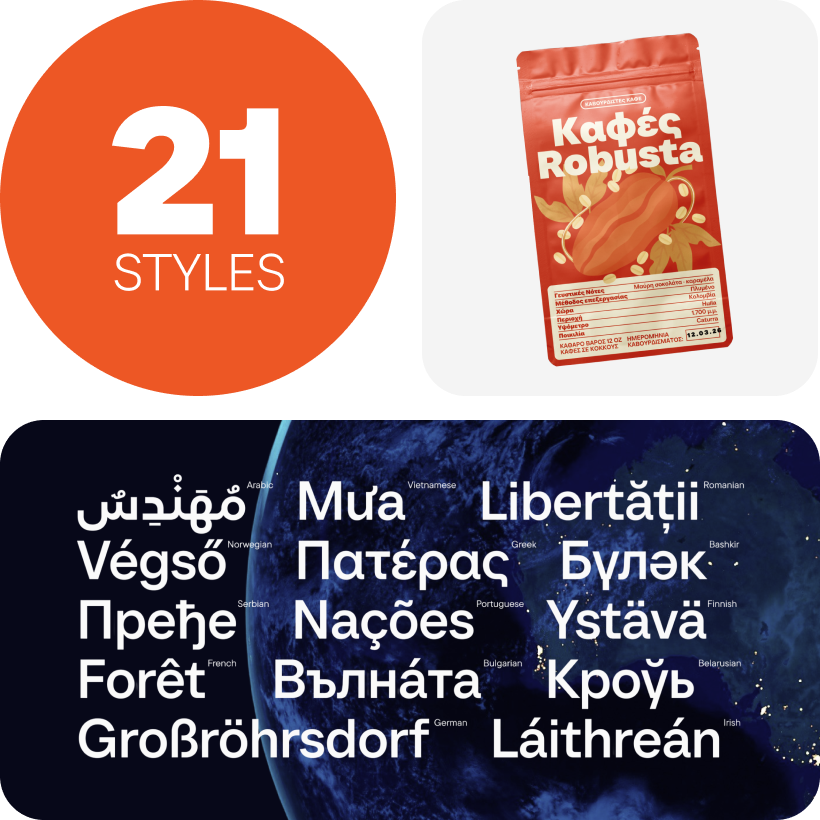
Шрифты для постеров к фильмам
TT Norms® Pro — TT Нормс Про
TT Norms® Pro — функциональный геометрический гротеск для эстетичных решений, бестселлер студии TypeType. Это стильный, лаконичный и универсальный шрифт, который станет полноценной базой для вашей коллекции.
TT Commons™ Pro — TT Коммонс Про
TT Commons™ Pro — геометрический гротеск. Один из самых востребованных шрифтов студии, получивший признание за счёт универсального характера, объёмного кассового состава с поддержкой более 280 языков и функционального набора OpenType фич.
TT Hoves Pro — ТТ Ховс Про
Произносится «ТТ Ховс Про». «Hoves» — производное слово от horizontal (с английского «горизонтальный») и vertical (с английского «вертикальный»). «Pro» произносится как «про», и является разговорным сокращением слова «профессиональный». Буквы «TT» являются аббревиатурой названия компании.
TT Hoves Pro — один из бестселлеров нашей студии, входящий в «базовую» коллекцию универсальных шрифтов. Это скандинавский гротеск с нейтральным, и при этом узнаваемым характером.
TT Odellia — ТТ Оделлия
Произносится «ТТ Оделлия». Слово «Odellia» — производное от имён Одетта и Одиллия из балета «Лебединое озеро». Буквы TT являются аббревиатурой названия компании.
TT Odellia — старостильная антиква с современным рисунком, вдохновлённая венецианскими шрифтами и классической музыкой.
TT Nooks Serif — ТТ Нукс Сериф
Произносится «ТТ Нукс Сериф». «Nooks» — производное слово от nook, в переводе с английского «закоулок». «Serif» произносится как «сериф», в переводе с английского «антиква». Буквы «TT» являются аббревиатурой названия компании.
TT Nooks Serif — акцидентная новостильная антиква с лёгким налётом эгоцентричности. У неё острый и твёрдый, при этом элегантный и статный характер.
TT Chocolates — ТТ Чоколитс
Произносится «ТТ Чоколитс». «Chocolates» — производное слово от chocolate, в переводе с английского «шоколад». Буквы «TT» являются аббревиатурой названия компании.
TT Chocolates — изящный гуманистический гротеск сo сбалансированными пропорциями, близкими к классическим. Шрифт с приятным дружелюбным характером, который интуитивно воспринимается как что-то знакомое.
TT Nooks Script — ТТ Нукс Скрипт
Произносится «ТТ Нукс Скрипт». «Nooks» — производное слово от nook, в переводе с английского «закоулок». «Script» произносится как «скрипт», в переводе с английского «курсив». Буквы «TT» являются аббревиатурой названия компании.
TT Nooks Script — шрифт с уникальным рисунком, который не имеет прямых аналогов.
TT Qurdisma — ТТ Курдизма
Произносится «ТТ Курдизма». Слово «Qurdisma» происходит от греческого κούρδισμα, в переводе — «извилистый». Буквы TT являются аббревиатурой названия компании.
TT Qurdisma — узкий и плотный декоративный шрифт, напоминающий причудливое растение. Вьющиеся, плавные контуры рождают растительный орнамент.
TT Dott — ТТ Дотт
Произносится «ТТ Дотт». «Dott» — производное слово от dot, в переводе с английского «точка». Буквы «TT» являются аббревиатурой названия компании.
TT Dott — экспериментальный пиксельный гротеск, в котором за основу пикселя взят круг. Это пластичный и необычный акцидентный шрифт, вызывающий ассоциации одновременно с вышивкой и техно-вечеринками.
TT Modernoir — ТТ Модернуар
Произносится «ТТ Модернуар». «Modernoir» — производное слово от moderne (с французского «современный») и noir (с французского «чёрный»). Буквы «TT» являются аббревиатурой названия компании.
TT Modernoir — акцидентный гротеск с разноширинными пропорциями. Плавные линии и изящные формы ар-нуво в этом шрифте сочетаются с ритмичностью и импровизационной свободой джаза.